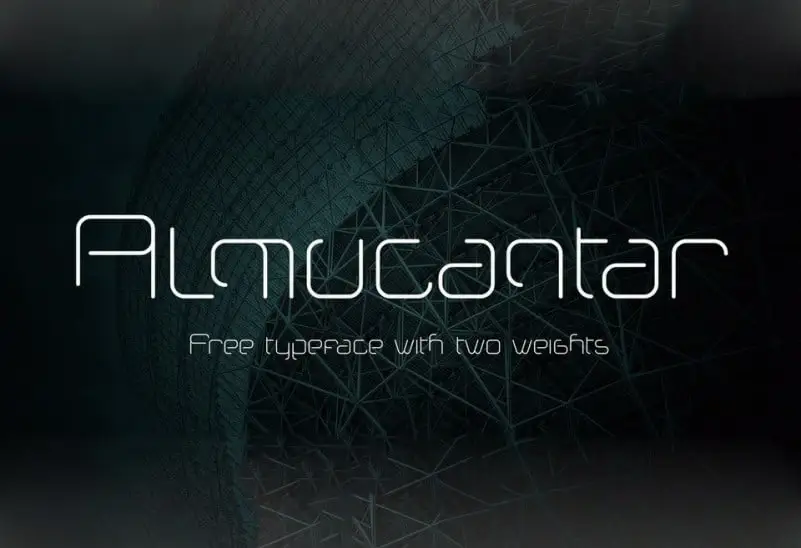
A Almucantar Display Font é uma fonte futurista com letras minimalistas e amplas. Desenvolvida pelo font designer Molten Core, esta família de tipo moderna traz um aspecto tecnológico e sci-fi. Ideal para aplicações em outdoors, headlines e design de logotipos, ela apresenta dois pesos de letra. Com seu olhar visionário sobre o design atual, a Almucantar Display Font é uma opção perfeita para aqueles que procuram uma mistura de minimalismo e tecnologia na sua identidade visual. Que tal incorporar um toque distante do mundo real em seus próximos projetos gráficos?